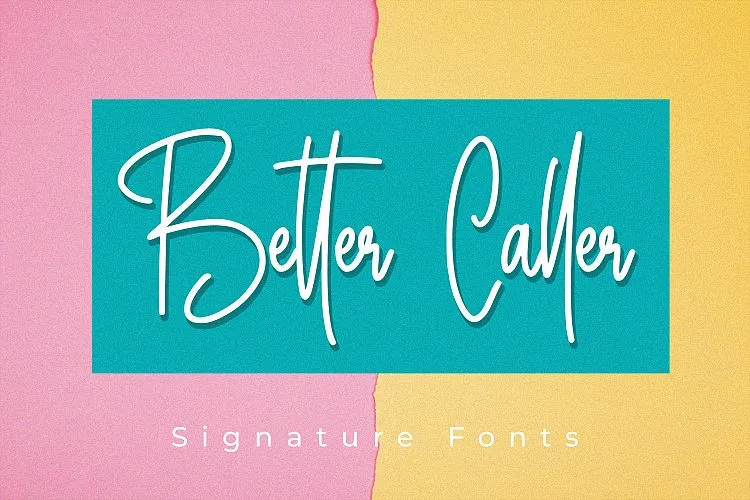
A nova fonte de cópia “Better Caller Signature Font” é uma escolha perfeita para aqueles que procuram adicionar um toque de elegância e feminilidade a seus projetos digitais. Esta opção de tipo, categorizada como fontes escritas à mão, é tanto moderna quanto natural, ideal para aplicar em diversos tipos de criações — desde selinhos de casamento até embalagens de produtos. Os arquitectos de cópia 24Design criaram esta fonte através de escrever realmente à mão, garantindo um resultado autêntico e único que vai deixar seu design ainda mais belo. Com uma fórmula perfeita entre elegância e graça fluida, “Better Caller Signature Font” é perfeitamente adequada para projetos que exigem um toque refinado — seja criação de logotipos, selinhos de casamento, embalagens ou qualquer outro projeto em que você deseja adicionar uma resolução sofisticada. Este tipo é o ideal para aqueles procurando por um padrão único e autêntico que complementará os seus esforços visuais de forma agradável e impecável.